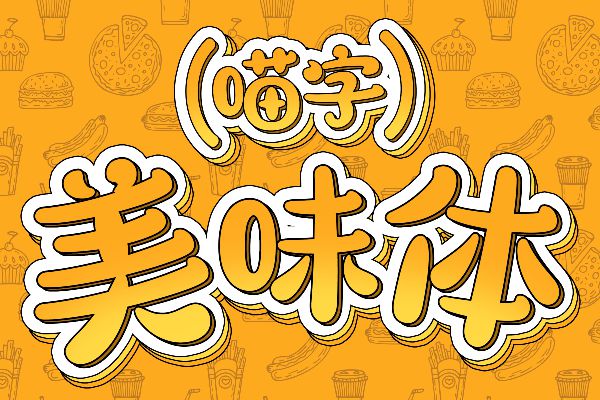
喵字美味体
一款精心为餐饮行业量身打造的特色字体库产品,它不仅体现了设计者对美食文化的独到理解和艺术创新,更深度融入了餐饮业的品牌个性与服务理念。其设计风格以圆润、饱满为核心要素,每一个笔画、每一个转折都流露出满满的温暖与丰盈感,营造出一种视觉上的舒适享受,让人仿佛能够感受到食物的鲜美和环境的温馨。